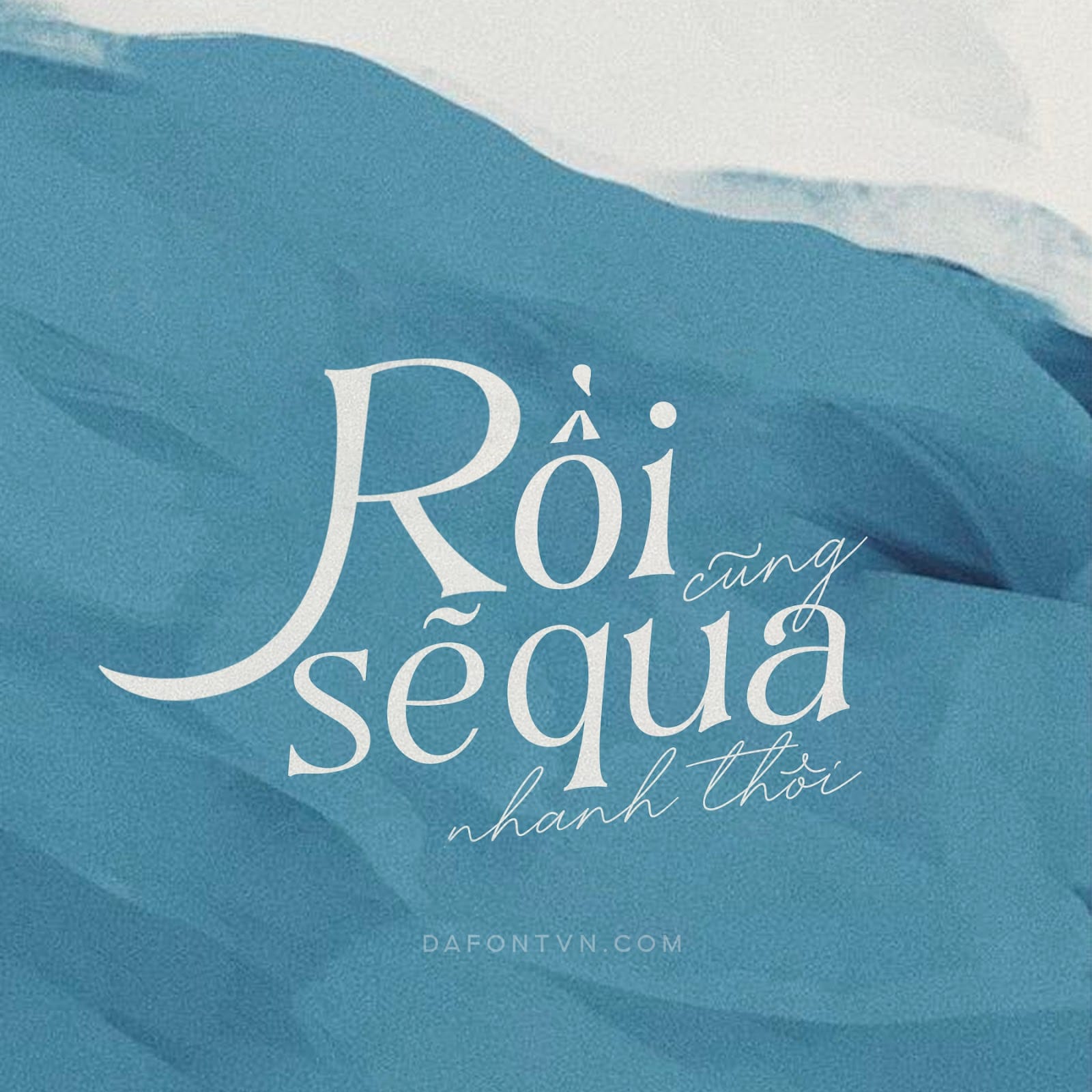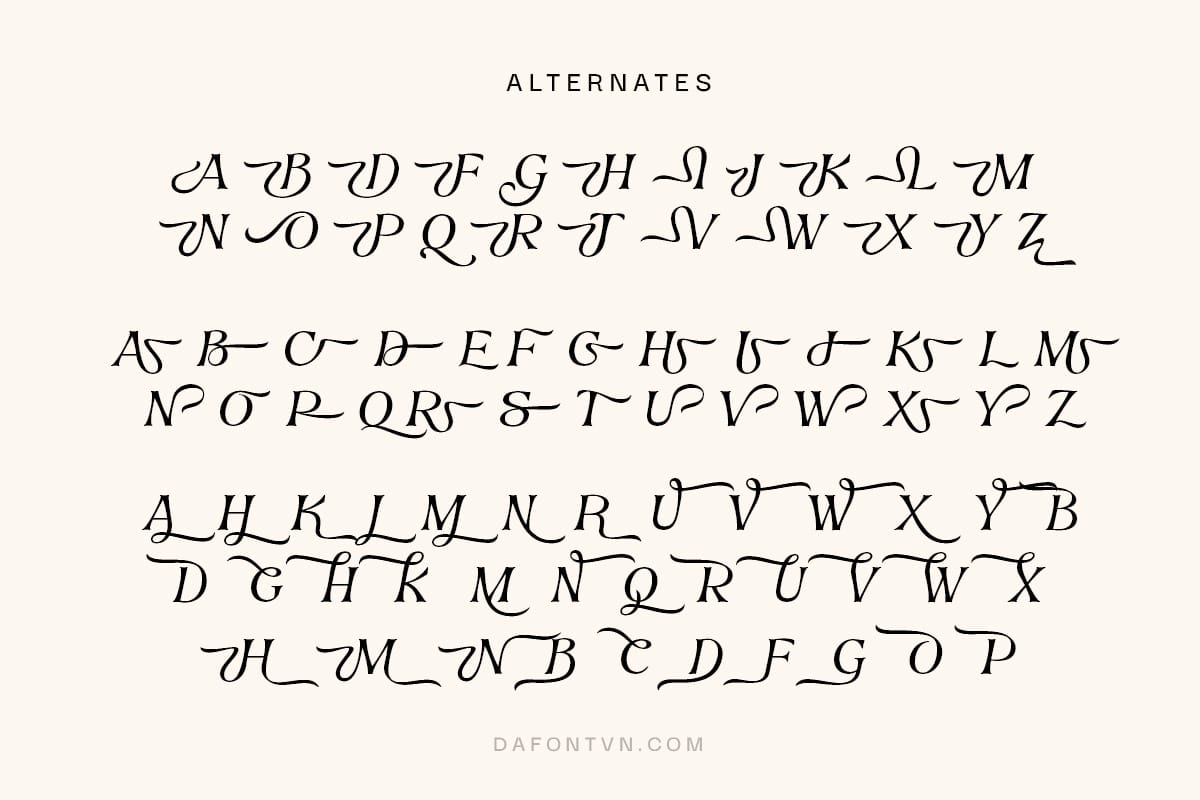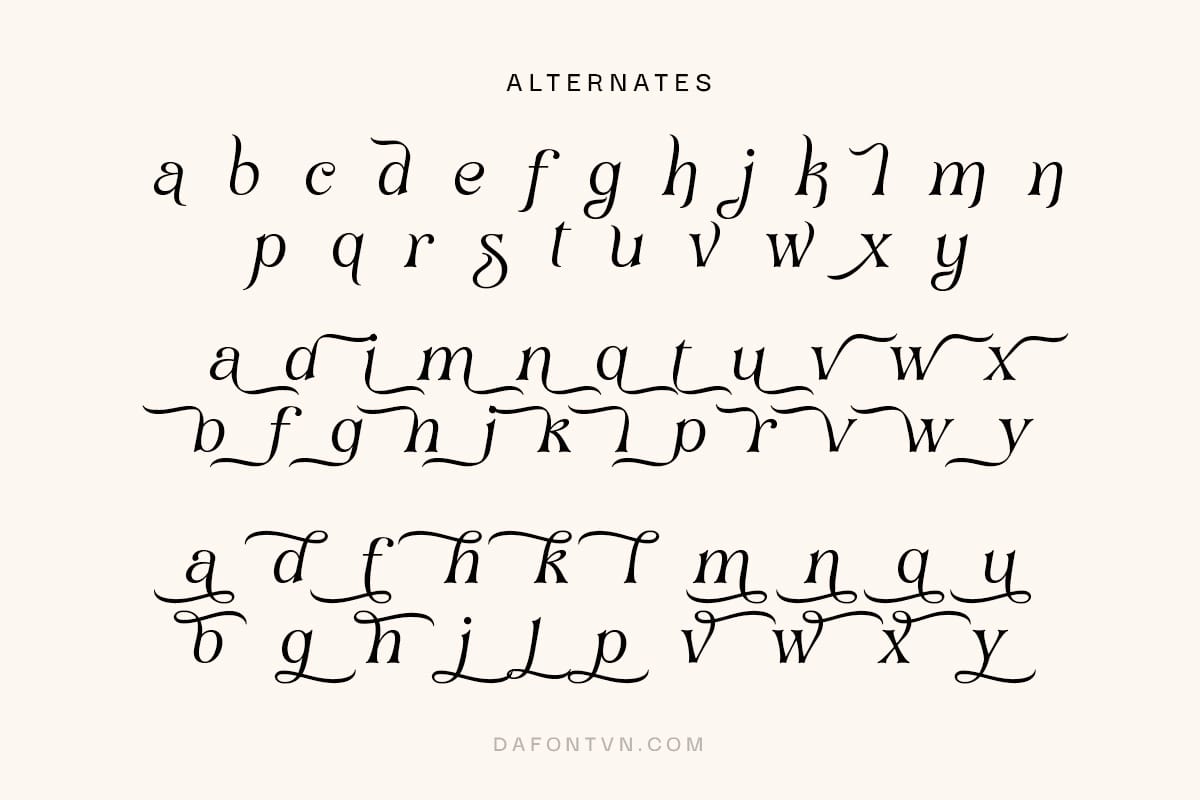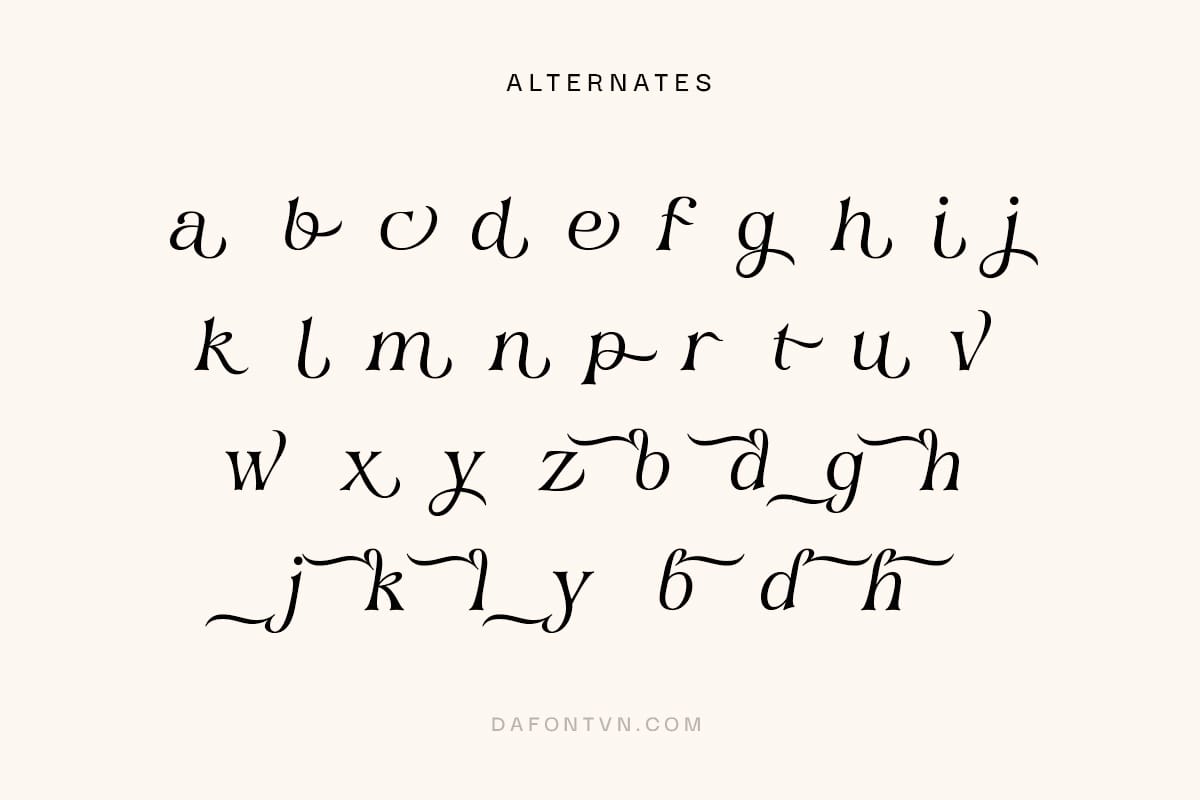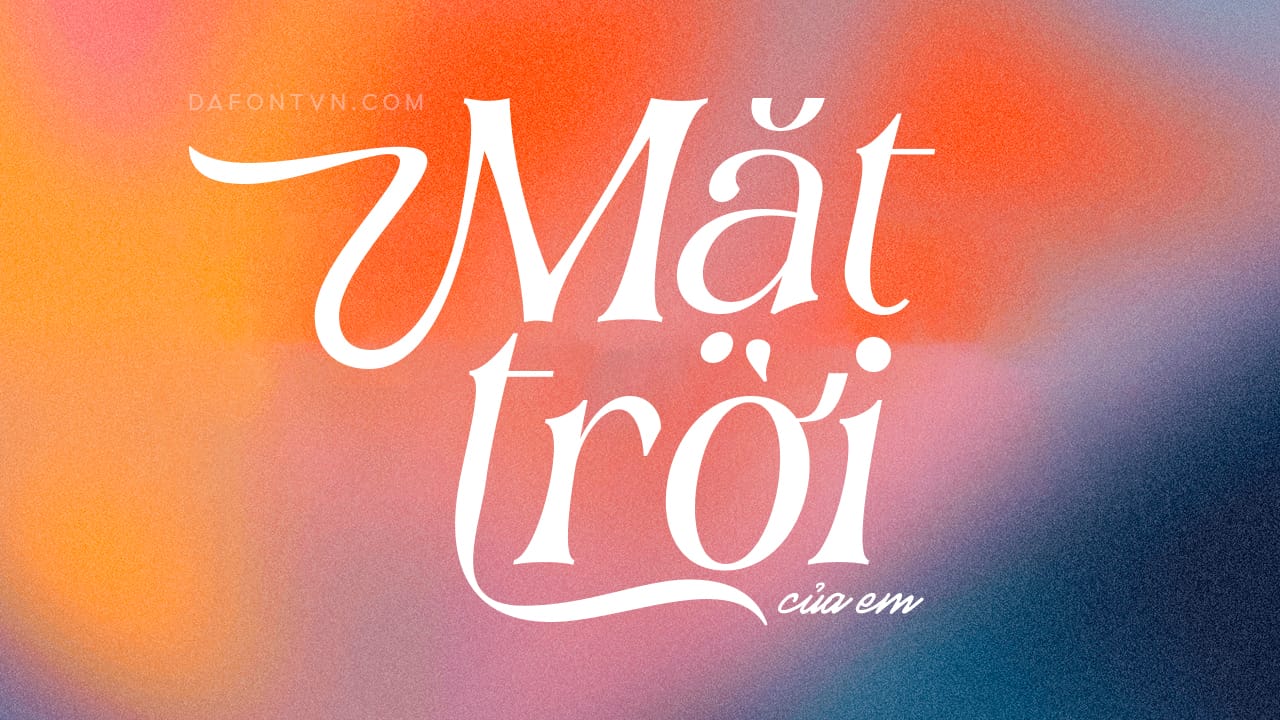
Font Mahony Browns mang phong cách hiện đại và năng động với các chữ được thiết kế nghiêng cùng với đó các chi tiết được thiết kế tỉ mỉ và mượt mà với các đường cong độc đáo và đẹp mắt. Vì vậy font chữ này rất dễ để áp dụng cho bất kỳ thiết kế nào, đặc biệt Mahony Browns đi kèm với hơn 717 glyph ở cả chữ hoa và chữ thường với nhiều tùy chọn thay thế độc đáo và thú vị.
Mahony Browns phù hợp cho các thiết kế như tạp chí, bìa sách, typography, thiệp mời, quảng cáo… hay bất kỳ thiết kế nào khác. Bạn nên sử dụng các glyph cũng như sử dụng font ở size lớn để font được hiển thị tốt hơn.
Mahony Browns font có hơn 717 glyph tuyệt đẹp ở cả chữ hoa và chữ thường để bạn tha hồ sáng tạo nhé.